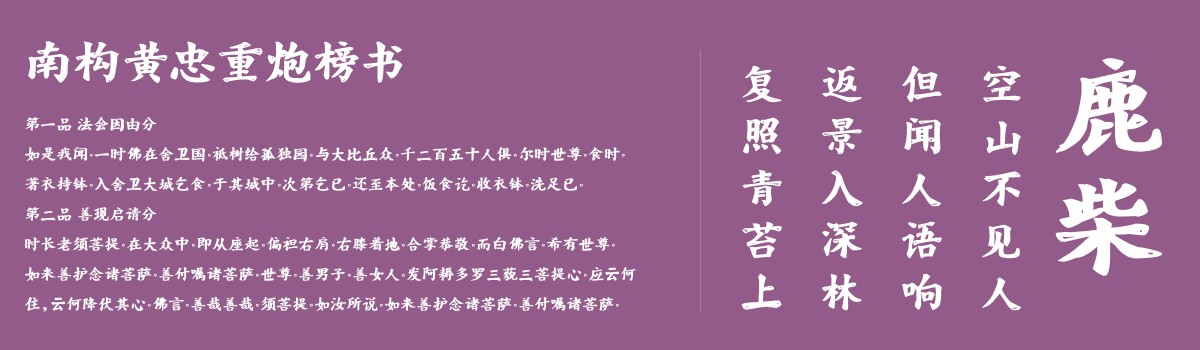
南构黄忠重炮榜书
这是一款榜书风格的毛笔书法类字体,非常适合用于标题大字以及对联呈现等,在众多的字体名称选择中,我们匹配了王者荣耀中的英雄同名人物黄忠,小编觉得黄忠是一个有正义感的,富有正能量的一位英雄人物,而这款字体也恰恰表达了这种精神,工整不阿,坚强而有力量的书风,是表达出了汉字字体对现代社会中某种事物的有机融合。